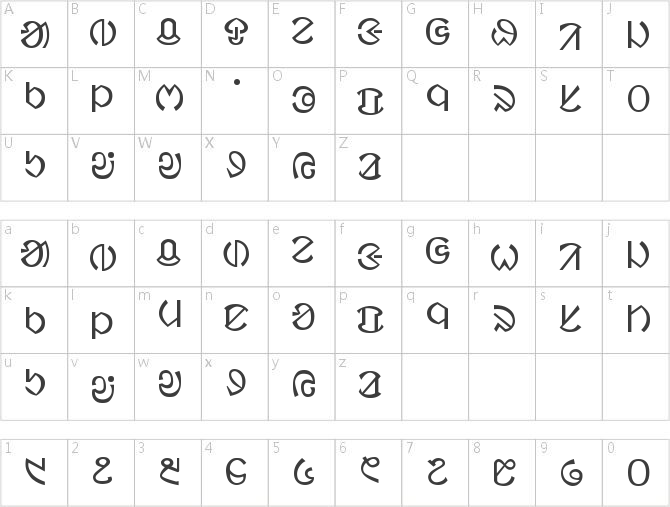
字體名稱: ol_ciki
ol_ciki_optimum(www.santalisong
ol_ciki_optimum(www.santalisong字體字庫是一款讓人賞心悅目、百看不厭的英文字體,適合各類廣告和產品包裝設計應用,字體大小0.02MB,格式為ttf字體,上傳用戶是多喝燙水,作者/版權方為未知